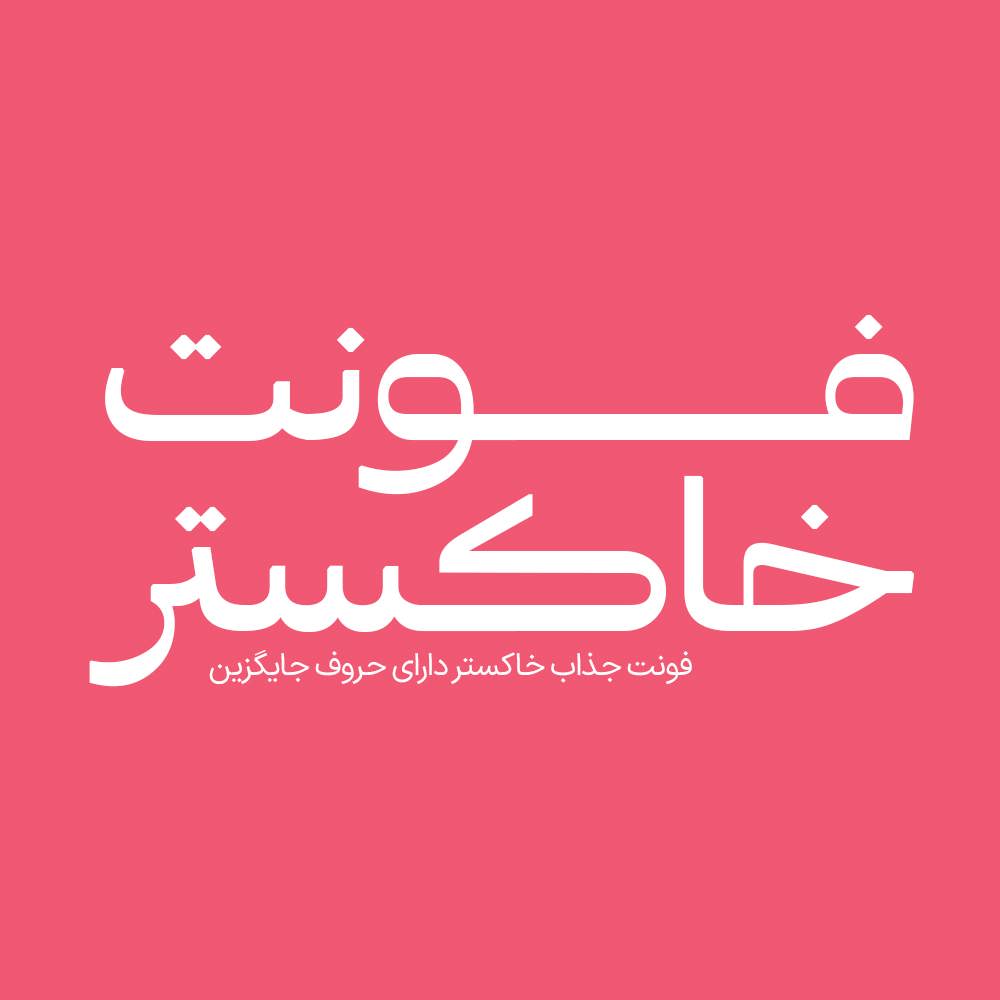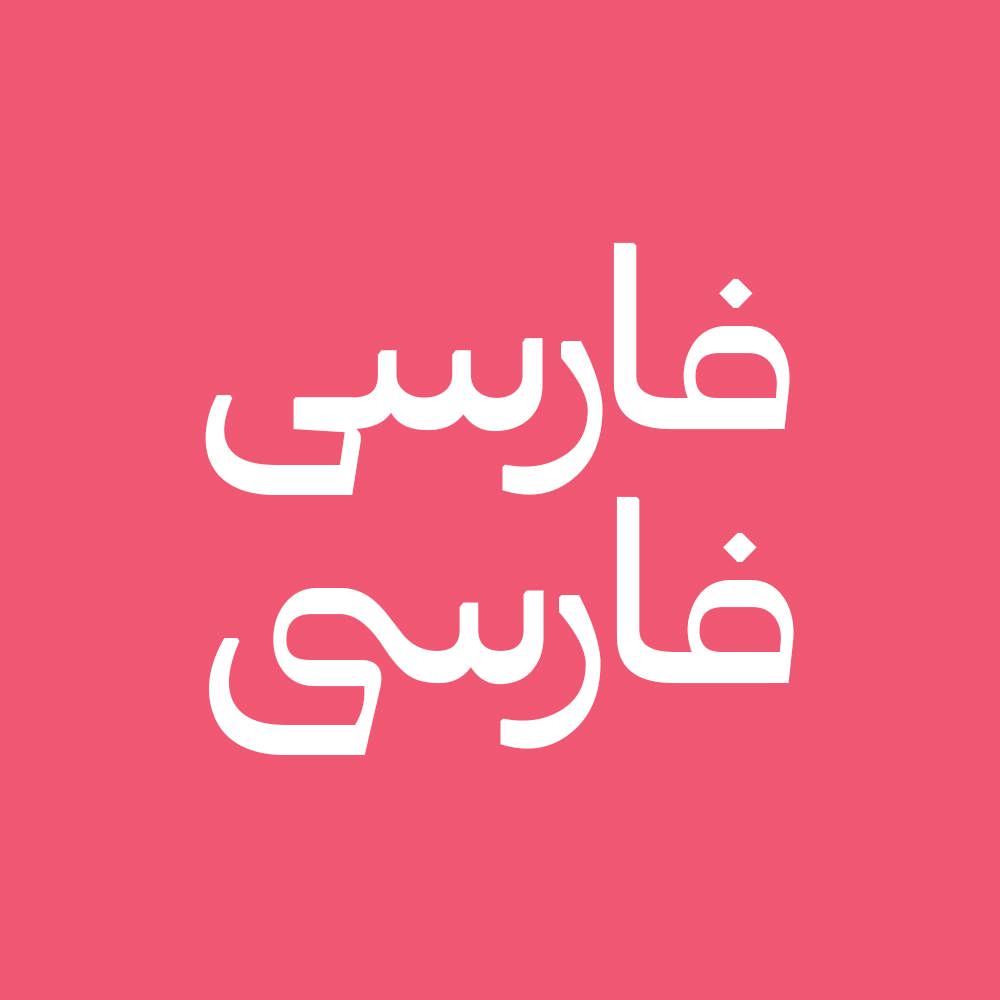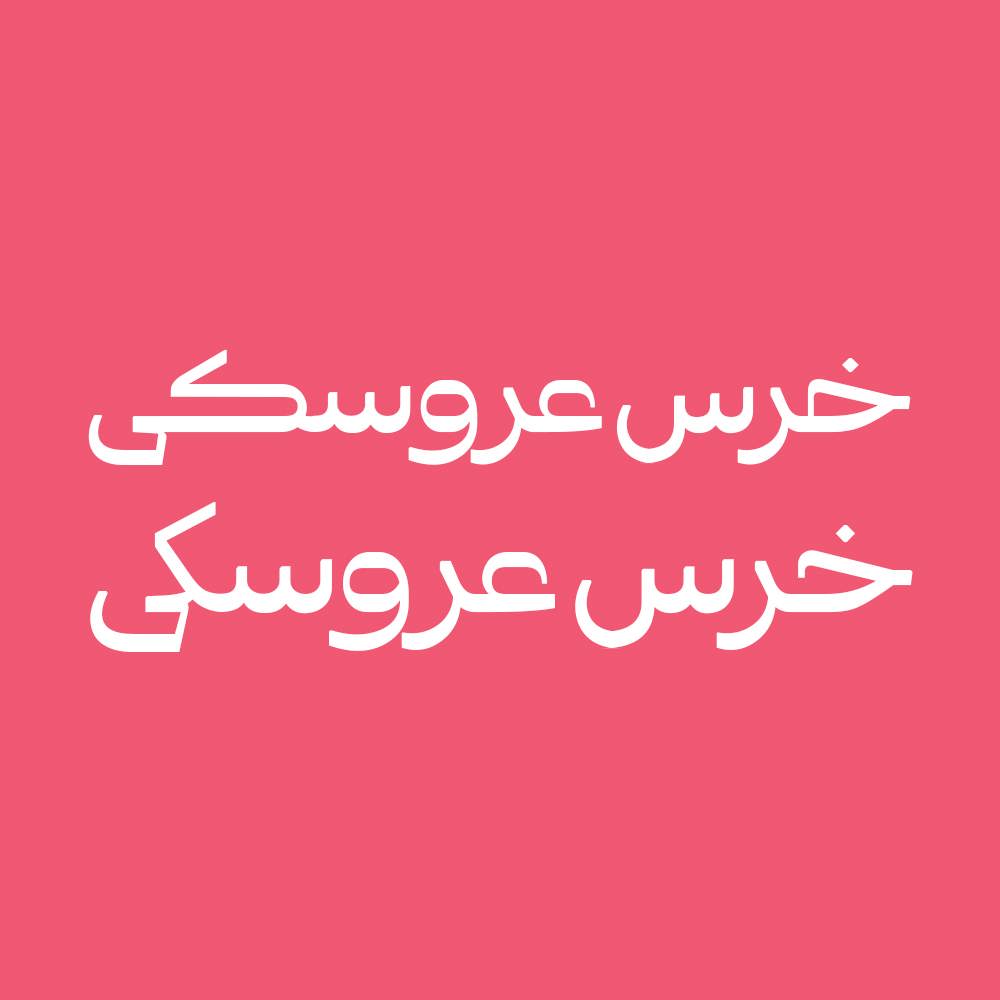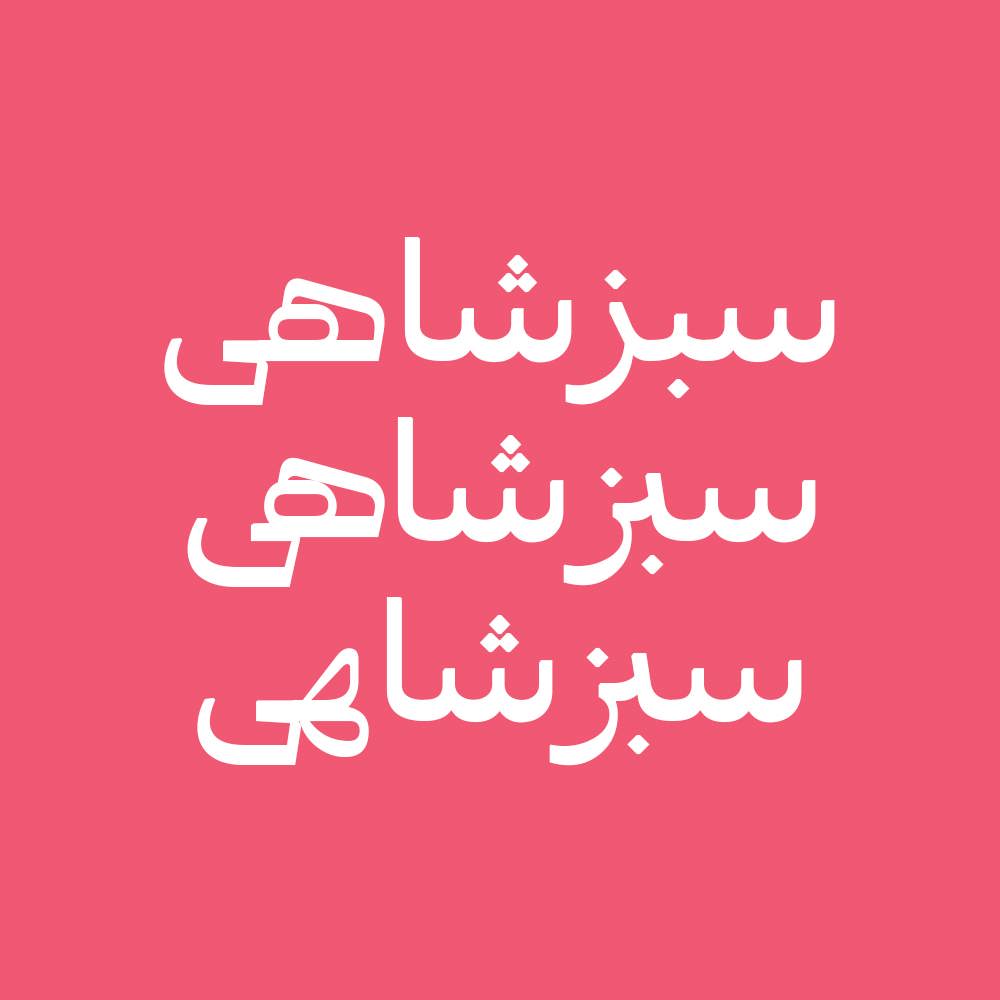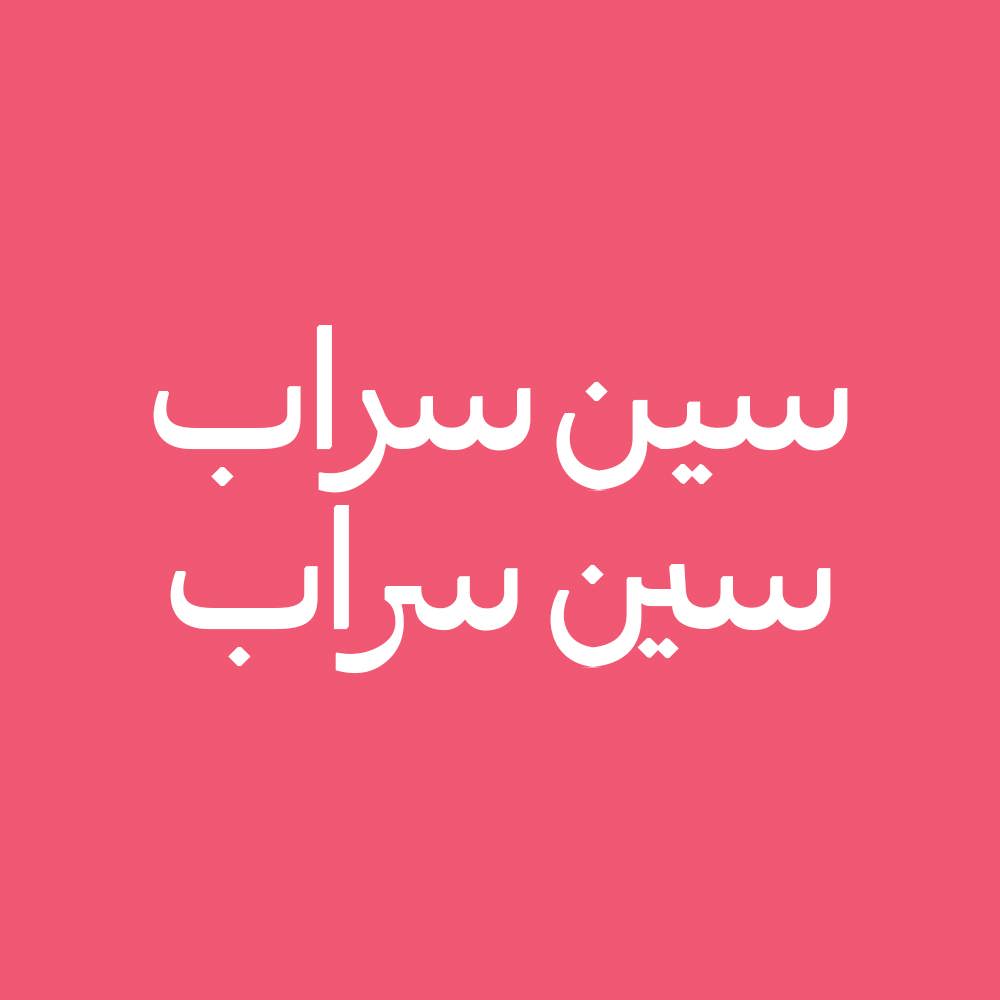
فونت فارسی خاکستر Khakestar Font
فونت فارسی خاکستر یک فونت تک وزن دارای حروف جایگزین با کاربرد طراحی لوگوتایپ و طراحی های مختلف همچون کتاب و تولید محتوای متن های کوتاه…
فونت فارسی خاکستر یک فونت تک وزن دارای حروف جایگزین با کاربرد طراحی لوگوتایپ و طراحی های مختلف همچون کتاب و تولید محتوای متن های کوتاه و بلند و عناوین می باشد. فونت خاکستر با ساختار حروف خود مناسب استفاده در لوگوهای نوشتاری می باشد. همچنین از فونت خاکستر در طراحی تابلوهای چلنیوم هم به دلیل ساختار منحصر به فردش می توانید استفاده کنید. فونت فارسی خاکستر زیبا و حرفه ای مناسب استفاده در عناوین و تیترها و جملات نسبتا کوتاه و هم طراحی انواع لوگوتایپ، تکست گرافی و استفاده در طراحی های خاص می باشد.
پیشنمایش و نمونه تایپ های فونت خاکستر